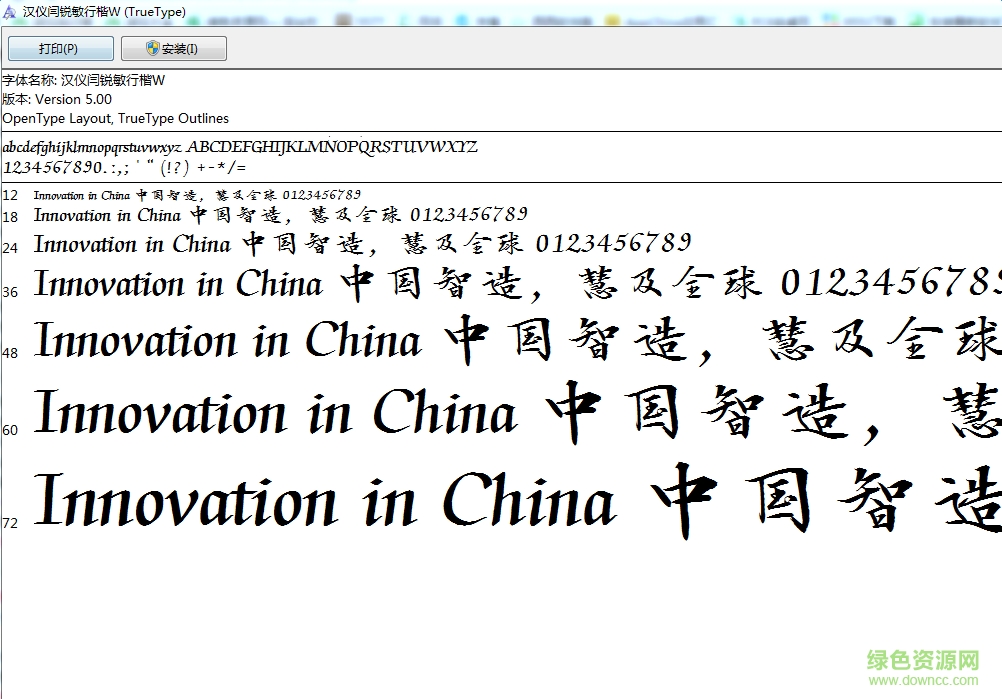
漢儀閆銳敏行楷是一款漢儀類行楷風(fēng)格字體軟件,行楷體筆畫灑脫,卻不失工整,完美闡釋了行楷酷炫風(fēng)格,深受廣大書法家喜愛(ài),還有更多好看字體歡迎來(lái)綠色資源網(wǎng)下載體驗(yàn)!
漢儀閆銳敏行楷體是一款商業(yè)字體,瀟灑帥氣的女性風(fēng)格字體,筆畫隨意卻不失工整,非常有韻味!